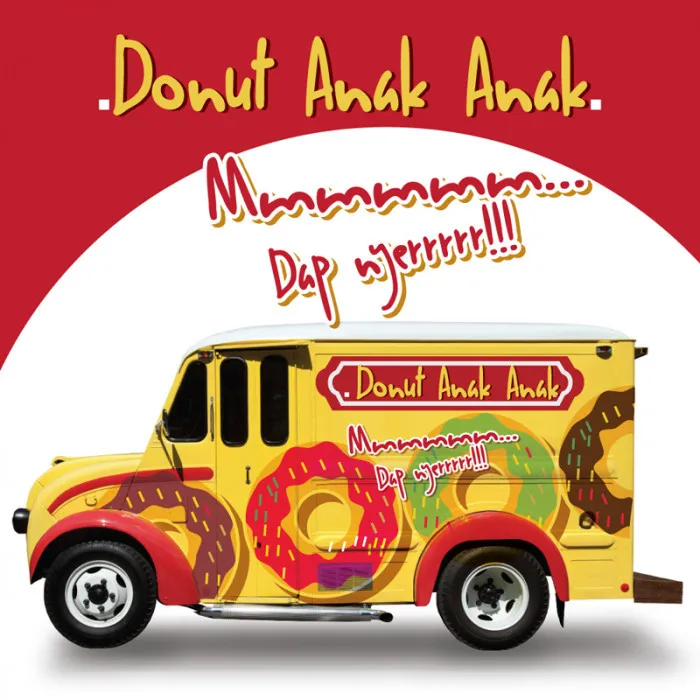
Anak Anak Font
Anak Anak é uma fonte criada por Haslinda Adnan que surgiu do amor pela escrita manuscrita. Com sua caligrafia fluida e delicada, esta fonte é perfeita para criações pessoais e de entretenimento. Mas, como qualquer bom artista gráfico deve respeitar o seu trabalho, caso deseje usá-la em propósitos comerciais, você precisa doar pelo menos $15 para Haslinda Adnan por meio do PayPal. Uma maneira de apoiar seus esforços e manter a qualidade deste talento único. Não importa se está criando uma aplicação web ou um poster publicitário: Anak Anak é uma escolha ótima, tanto pela sua elegância quanto pelo seu significado profundo para quem cria arte digital.